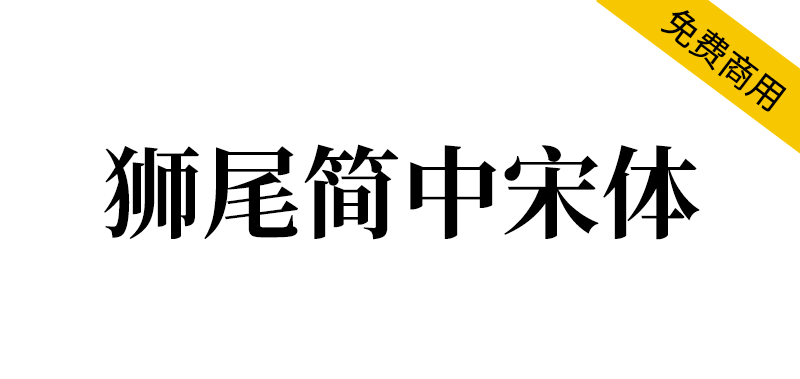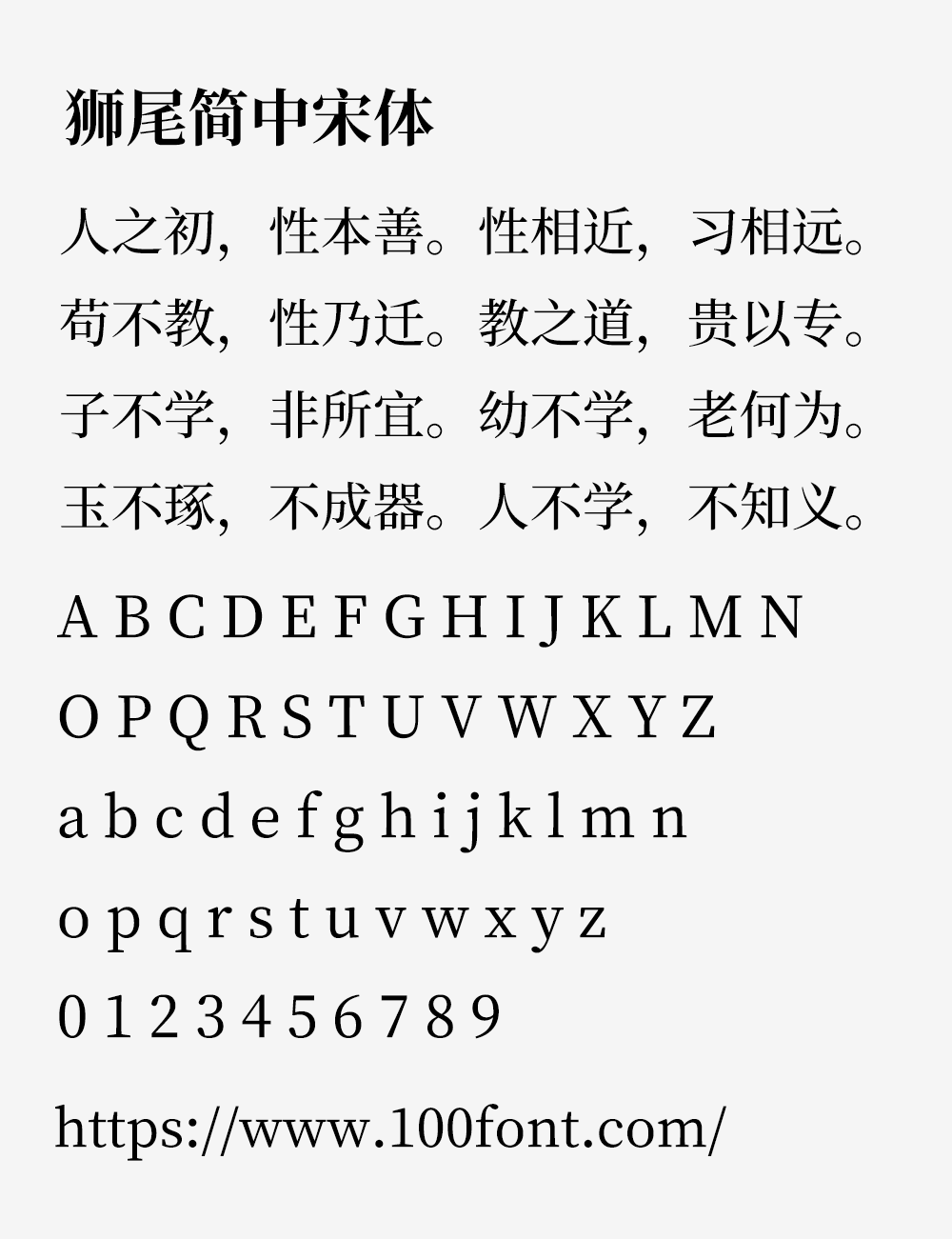
狮尾简中宋体基于思源宋体的繁转简字型(繁转简的意思就是输入繁体字时,会自动显示成简体字),狮尾简中宋体的特色是「繁体字转成简体字的字型档」,由于是转成简体,所以能处理「一简对多繁」。狮尾繁中宋体设计上针对笔画粗细有7种字重,所以不论大标、小标、简单的段落排版都能清晰辨识。可以免费商用,欢迎大家自由应用、自由优化、自由改作!